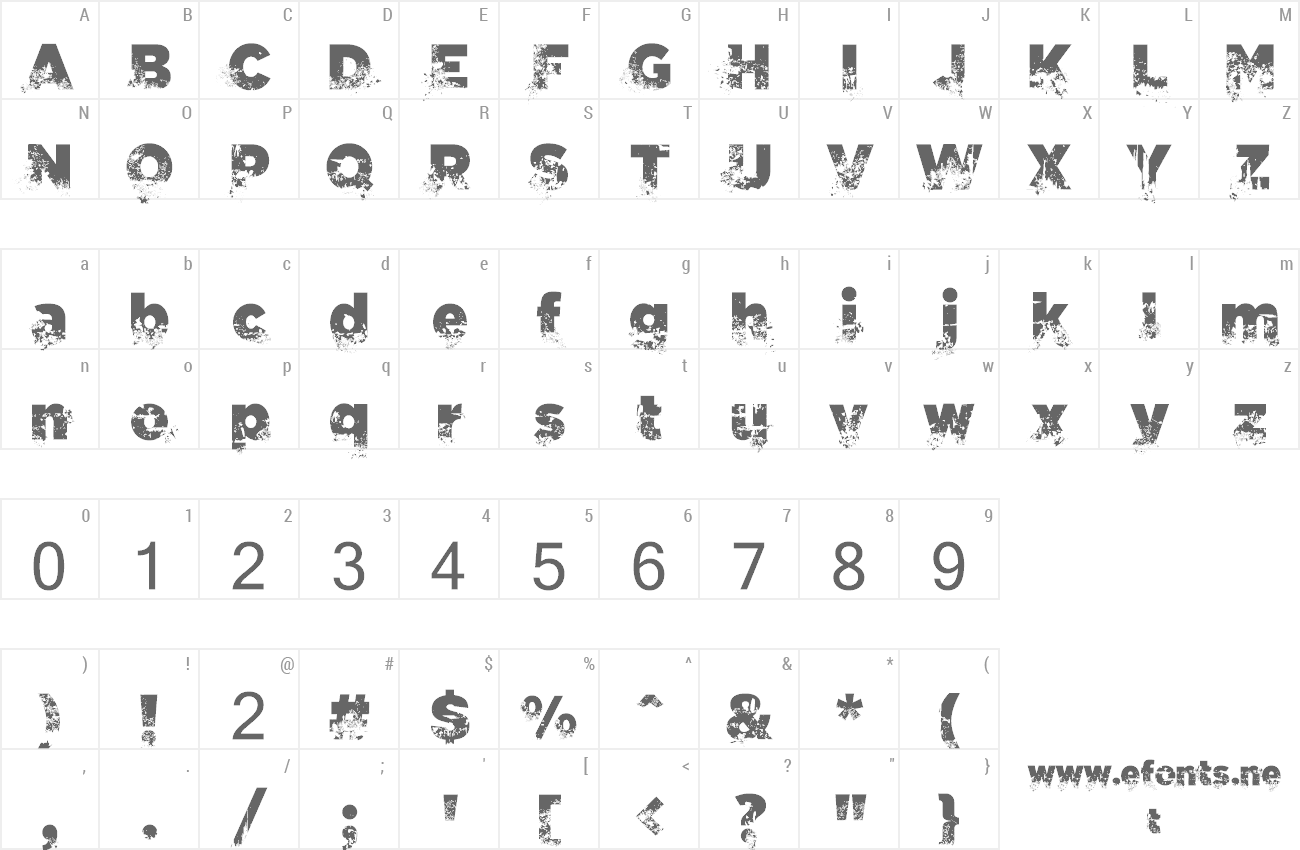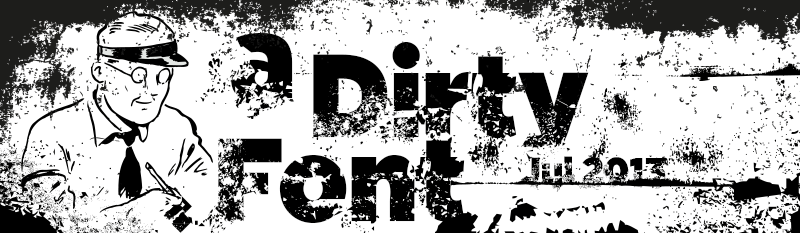
- Fuente sans, experimental, sucia y degradada, realizada en un ejercicio de deconstrucción violento y descuidado, en ella se puede apreciar el paso del tiempo y sus cicatrices, la huella de elementos naturales y otros que no lo son, un sumo proceso de bio degradación tipográfica. - Is a sans font, experimental, dirty and degraded, conducted an exercise in deconstruction violent and careless, it can be seen over time and its scars, the footprint of natural elements and others that are not, a high process of typographic biodegradation. Números disponibles en mi web / Numbers available on my website. • Descarga gratis las versión completa desde mi web. • Free download the complete version in my website. • Only for personal use. Sólo para uso personal. • Licencia comercial disponible / Available commercial license.>>https://defharo.com/fonts/cagatintas-dirty-font/ |